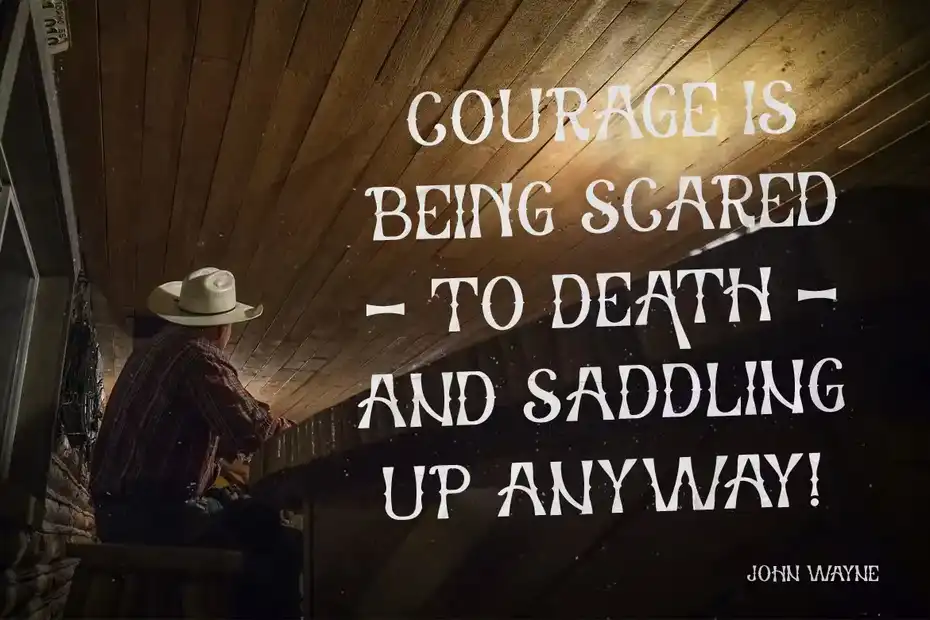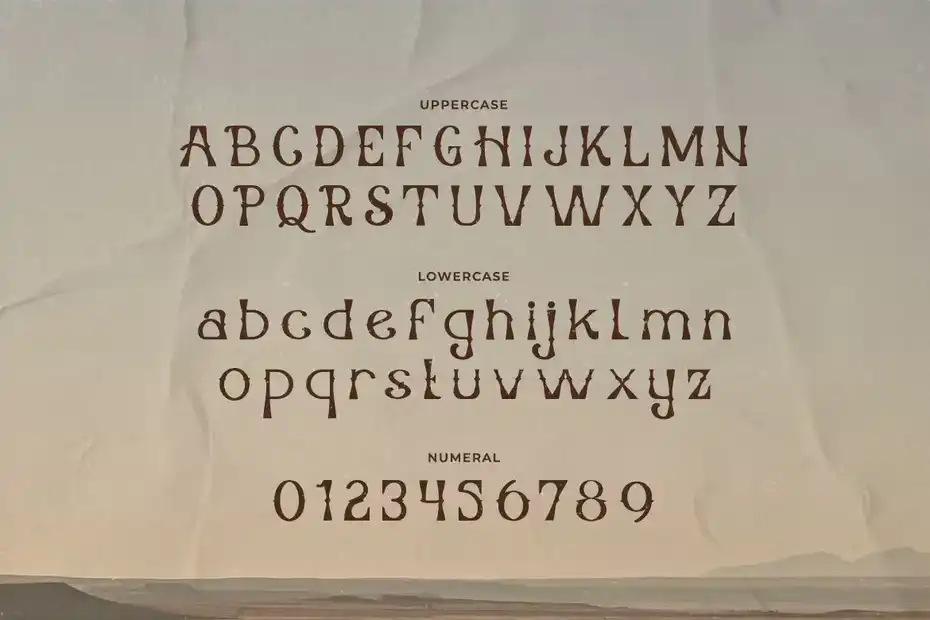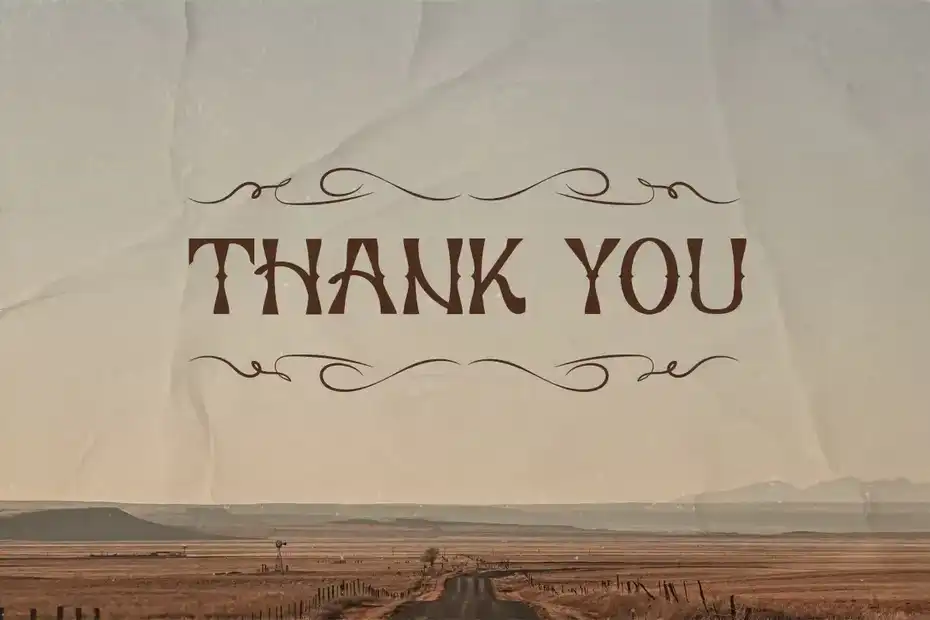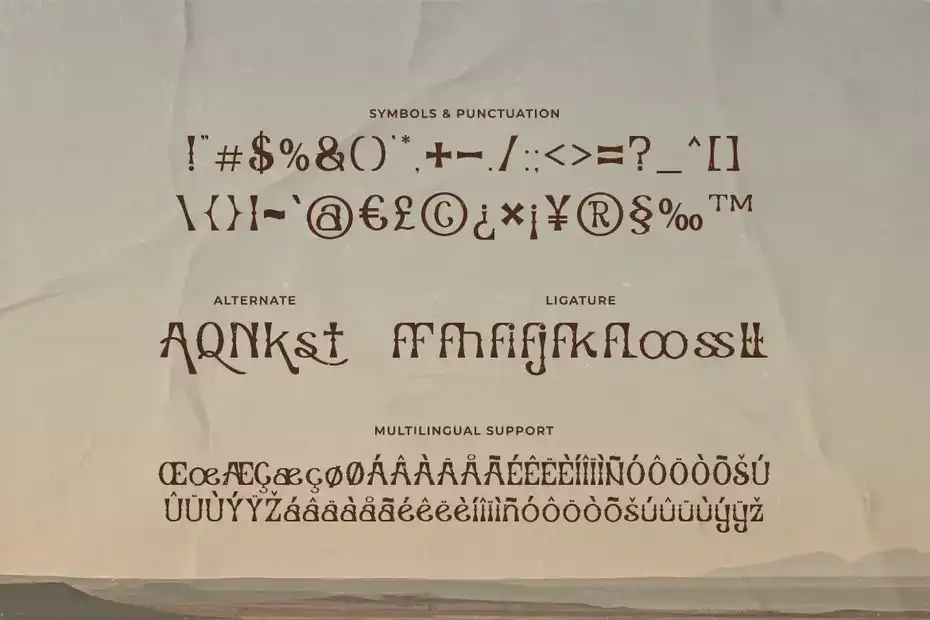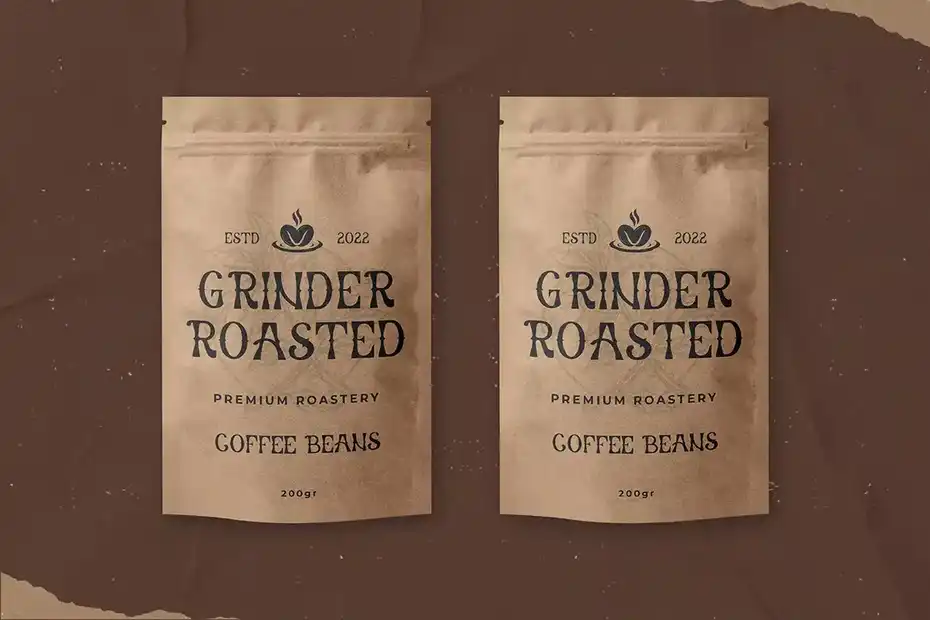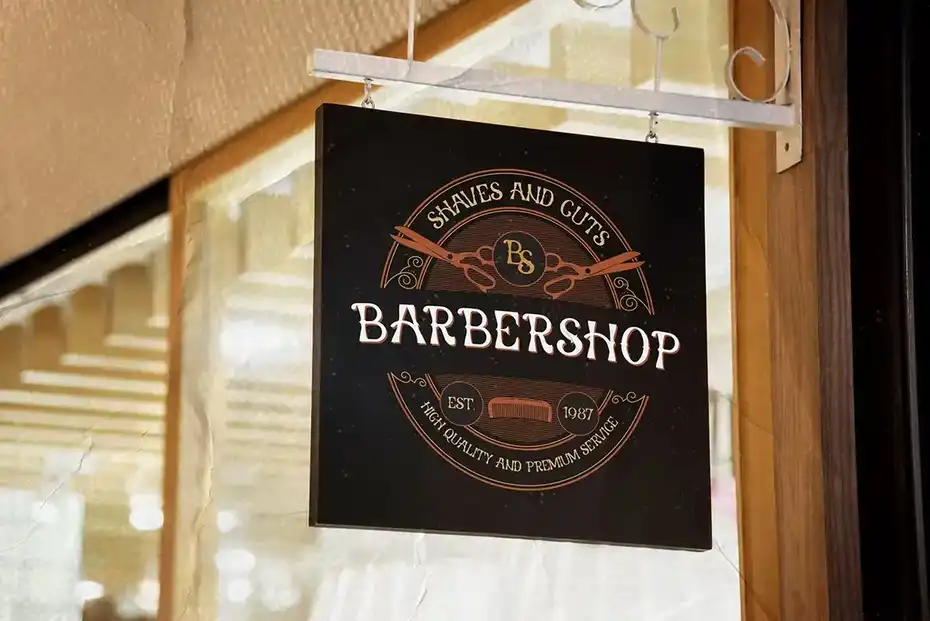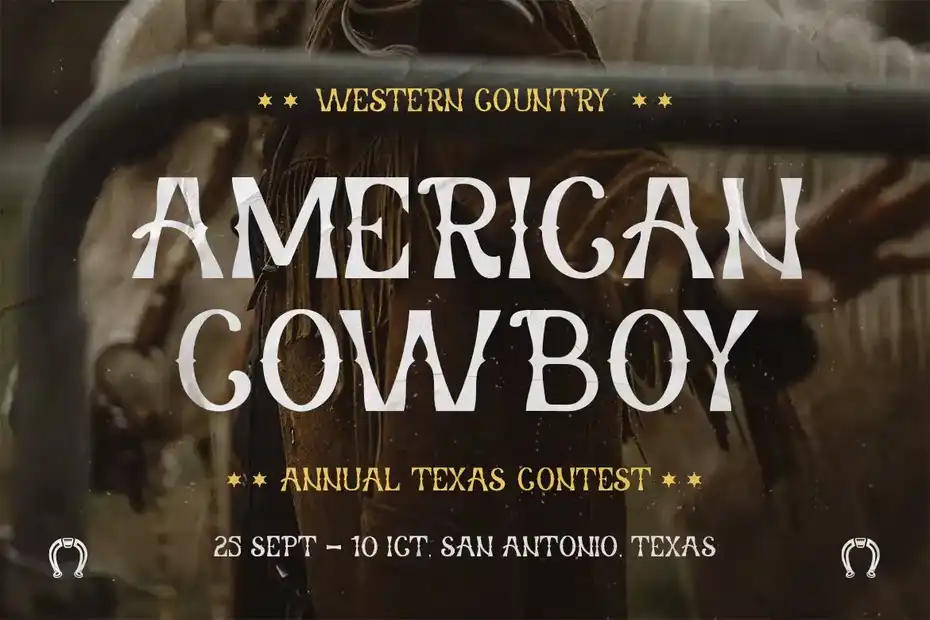
دانلود فونت وسترن Western of Dead – Western Display Typeface
دانلود فونت وسترن Western of Dead : این فونت انگلیسی یک فونت کلاسیک وسترن است که برای بازی‌ های کودکان، نقل‌ قول‌ ها، تایتل ها، لوگو، جلد کتاب، پوستر و غیره مناسب میباشد.